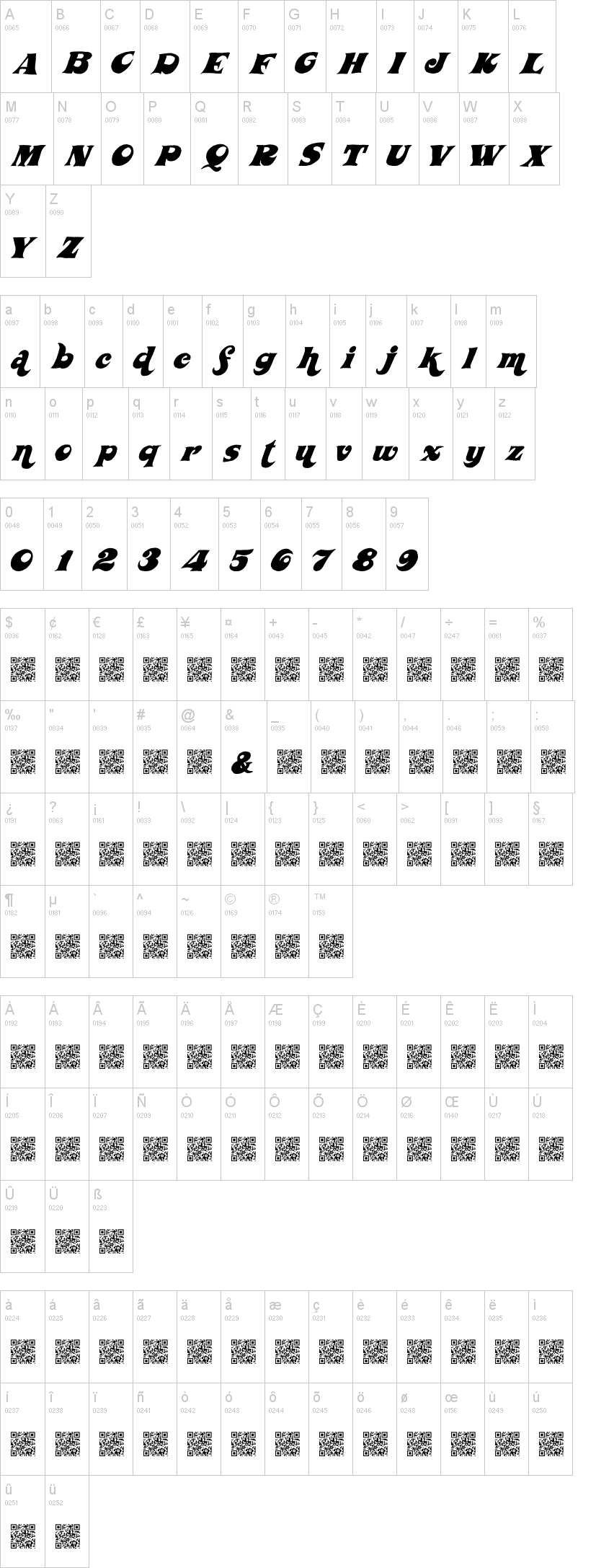
Wicked Seventies 是一款由著名的设计师Brian Bonislawsky设计的手写体字体。这款字体拥有一种温暖的、自然的、轻松的气息,它的笔画曲折优美,极具表现力,是一款非常适合用于海报、标识、标题和logo等设计的字体。它的字形清晰,具有良好的可读性,具有良好的结构,可以提供良好的视觉效果。内容介绍
Wicked Seventies是一款非常不错的手写艺术字体,具有很好的视觉感,适合于文化类的宣传设计、商业类品牌的广告和产品包装设计以及个性化文字排版等较多场景。